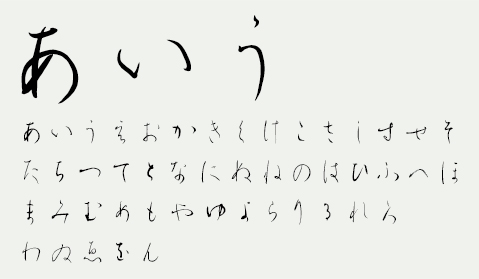
仮名の名手・紀貫之が揮毫したと言われる、かな最高峰の書風
『高野切』を元に作成しました(ひらがなのみのフォントです)
ウェイト見本
- NSK高野切第一種フォント/w1
- NSK高野切第一種フォント/w2
- NSK高野切第一種フォント/w3
- NSK高野切第一種フォント/w4
- NSK高野切第一種フォント/w5